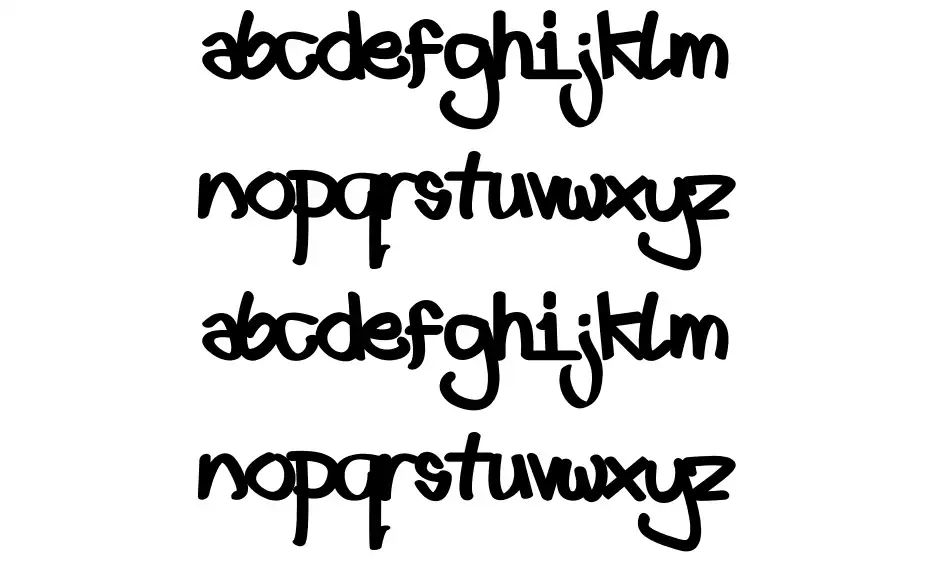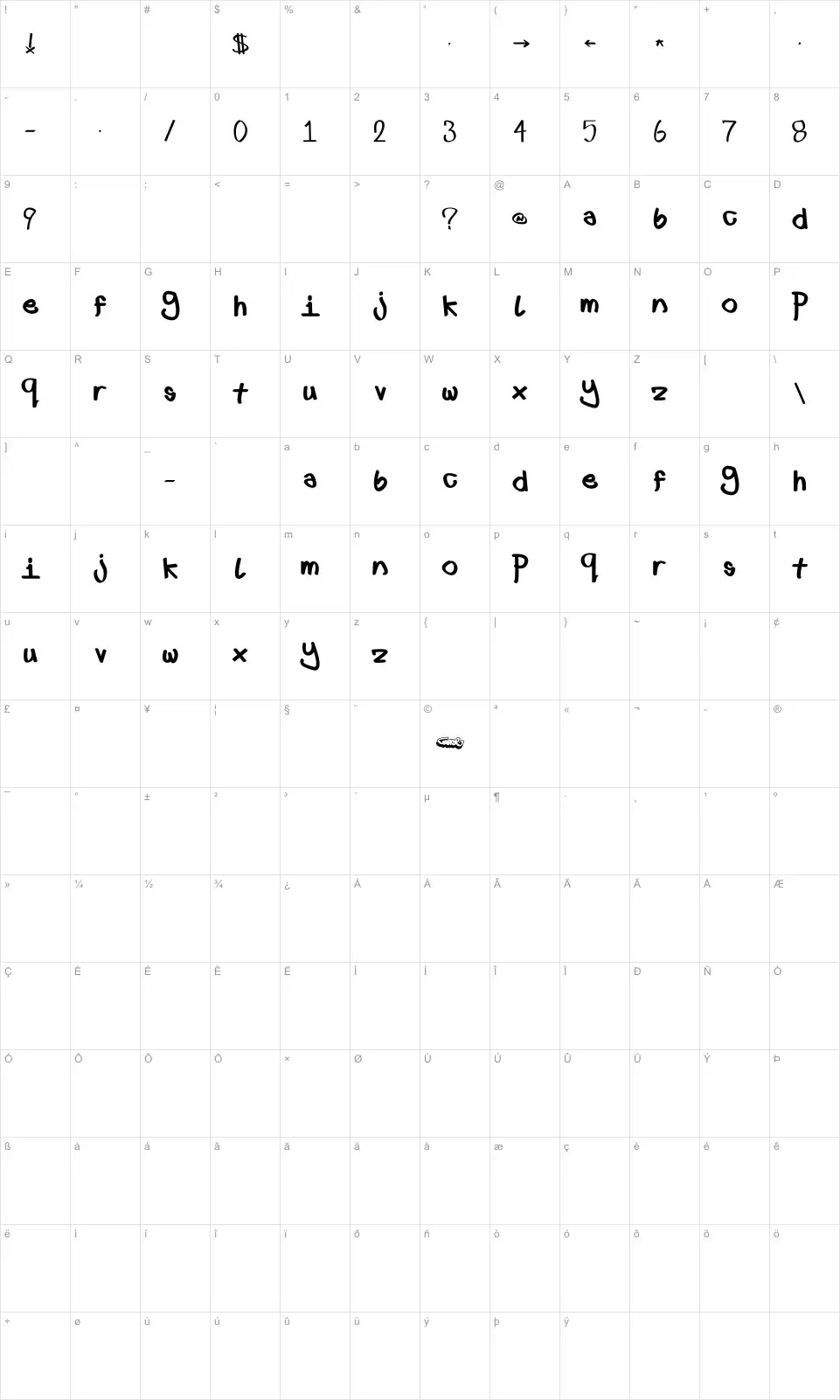
First font lower fat – Download Grátis
A First font lower fat é uma fonte script graffiti desenvolvida pelo designer CrazeCo.com.au, disponível gratuitamente para uso pessoal. Adicionada em 12 de julho de 2022, essa fonte tem uma forma compacta e elegante, perfeita para criar um estilo único em seus projetos. Se você estiver procurando pela First font lower fat, ou simplesmente gostando do design script da CrazeCo.com.au, você pode agora baixar e usá-la ou até gerar um preview de texto personalizado para experimentar antes de usar, tudo online. Esta fonte, de formato TTF, tem 29 KB de tamanho e é parte da categoria Graffiti, dando um toque moderno e inovador aos seus projetos de design. Convidamos você a explorar e experimentar a First font lower fat, uma escolha de fontes de graça que certamente enriquecerá suas criações. Visite o website do designer na página https://CrazeCo.com.au para mais informações e novidades.